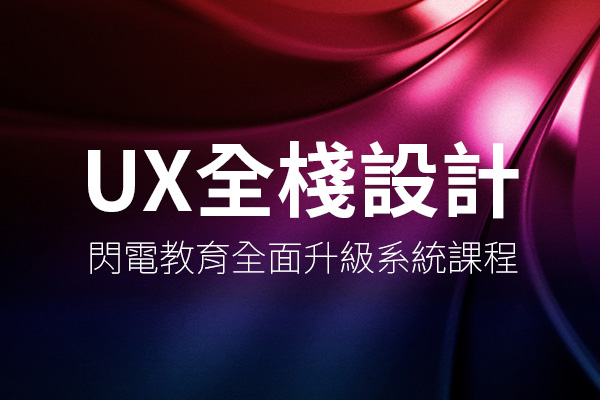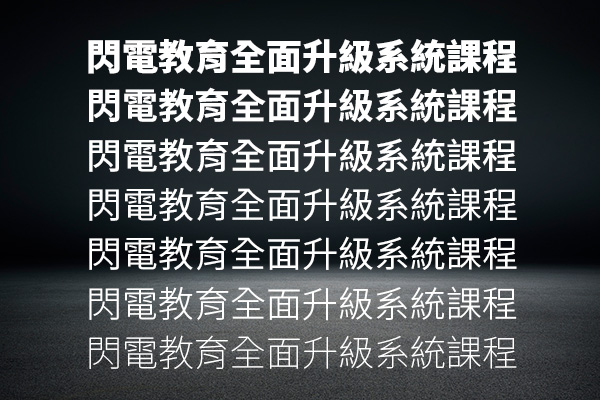
思源黑体-繁体中文版
思源黑体-繁体中文版是由Adobe与谷歌携手开发的开源字体,自2014年问世以来,经过不断的修正与完善,其影响力日益扩大。像思源柔黑、思源真黑等字体都是在该开源的基础上衍生而来,具有很高的实用性。
这款字体拥有七种字体粗细(ExtraLight、Light、Normal、Regular、Medium、Bold和Heavy),完全支持日文、韩文、繁体中文和简体中文。此外,它还包括来自Source Sans字体家族的拉丁文、希腊文和西里尔文字形,共计65536个字形。Google将其命名为Noto SansCJK,作为Google的Noto字体家族的一员。Adobe则将其命名为Source Han Sans,成为Adobe的Source字体家族的一员。需要强调的是,Adobe拥有该字体的设计版权。而发布的字体文件则可以不受限制地免费使用。
思源黑体-繁体中文版的开发旨在实现全球语言文字的兼容性和通用性。它不仅适用于中文排版,还支持多种语言文字的排版。这款字体在设计和使用上具有广泛的适用性,无论是用于印刷品、网站设计还是移动应用开发,都能呈现出清晰、流畅的视觉效果。